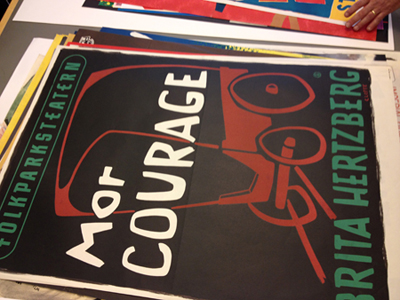
Gilleskväll om William Morris på KB
Den 21 och den 26 mars besökte sammanlagt ett 25-tal medlemmar Kungliga Biblioteket för att stifta närmare bekantskap med bibliotekets samling av böcker av tryckta och/eller skrivna av William Morris. Morris som var en av Arts and Craft rörelsens förgrundsfigurer och drev under sina sista år den legendariska Kelmscott Press, som tryckte bland annat mästerprovet som Chaucer’s Canterbury Tales. Gillets medlemmar fick stifta bekantskap med tryckeriets tre typsnitt, Troy, Chaucer och Golden type samt böckernas fantastiska papperskvalitet och underbara träsnitt.
Morris på KB
Gilleskväll 28/11: Bilden, bokstaven, boken
Christer Jonson presenterar och berättat om sin nya bok Bilden, bokstaven, boken – att förvalta en tradition.
Välkommen på ett samtal om att förvalta vår tradition.
Julgille i Gamla stan
Julgille onsdagen den 5 december 2012 på restaurang Treskillingen, Lilla nygatan 6 (inne i Postmuseet).
Gilleskväll 22/11: Valter Falks samling
Gillets medlemmar välkomnas till Kungliga biblioteket för att ta del av Valter Falks samling av typografisk litteratur.
Ingrid Svensson från KB berättar om Valter Falk, författaren till standardverket Bokstavsformer & typsnitt genom tiderna, och visar delar av hans omfattande samling av böcker, typprover och provböcker.
Gilleskväll: Vart är typografin på väg?
En diskussionskväll med sikte på framtiden och tro på att förändringar alltid innebär nya möjligheter. Programidé av Arne Heine som har lovat att tända de första facklorna.
Vad är typografi – egentligen?
Vem har idag rätten att kalla sig för typograf?
Var finns typograferna när tekniken skapar nya behov?
Och vem fan betalar för typografisk kvalitet?
Ordet är fritt & ditt
PS. Slipa dina argument!
A B C å allt om D
Nästa gillessammankomst bli torsdag 4 oktober klockan 18–20. Då berättar gillesmedlemmen Nina Ulmaja om arbetet med sin bok A B C å allt om D. Det blir en djupdykning i bokstävernas historia och människans viktigaste uppfinning – alfabetet. Platsen är Antikvariat Morris på Hantverkargatan 21.
Årsmöte 2012
Torsdagen 7 juni med start klockan 17.45 går Stockholms Typografiska Gilles årsmöte 2012 av stapeln. Platsen är Nyloftet på Skansen där det kommer serveras ett traditionsenligt sillbord.
Gilleskväll bland affischer på KB